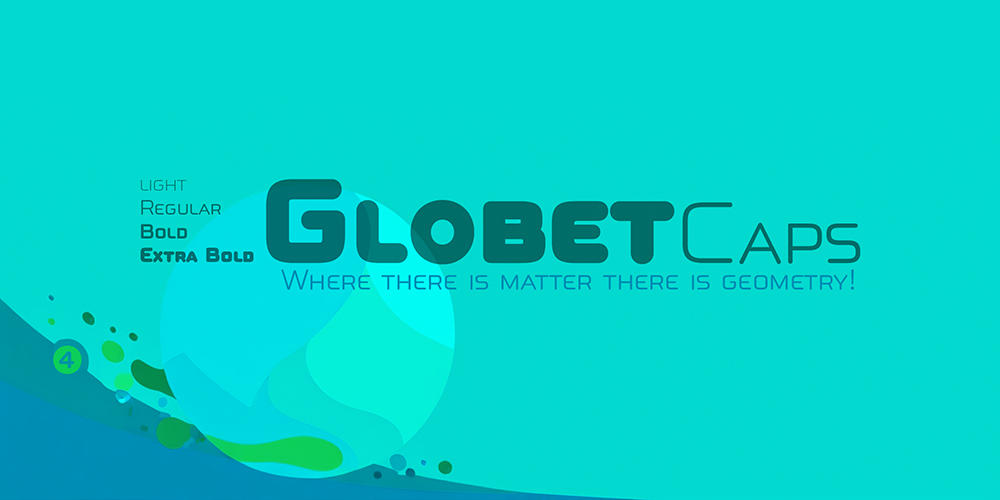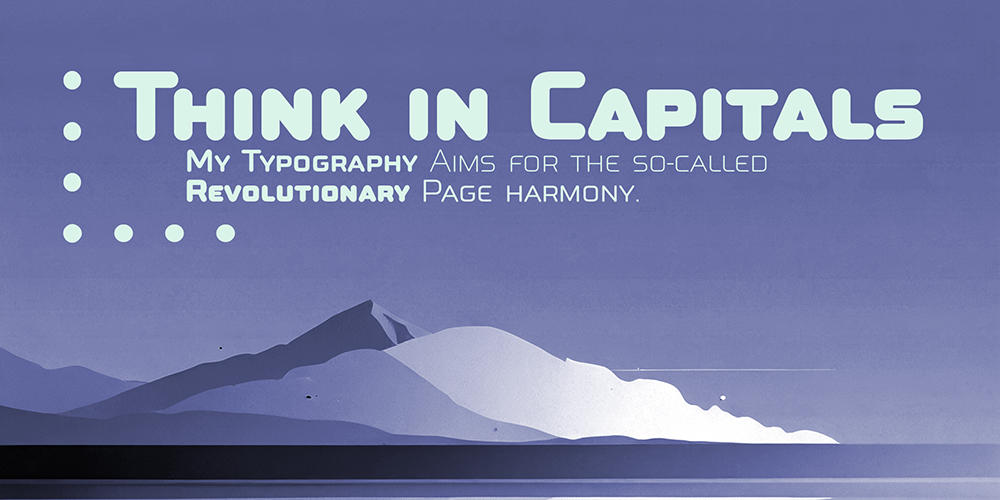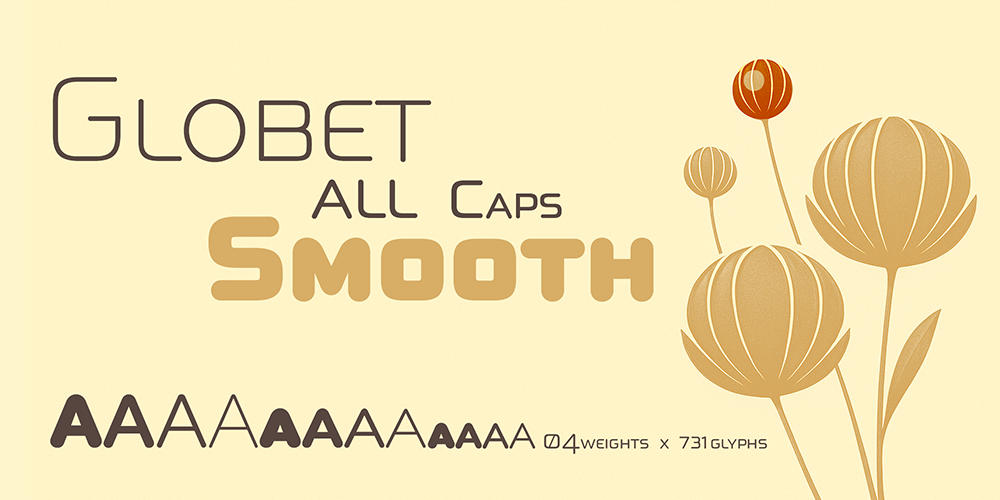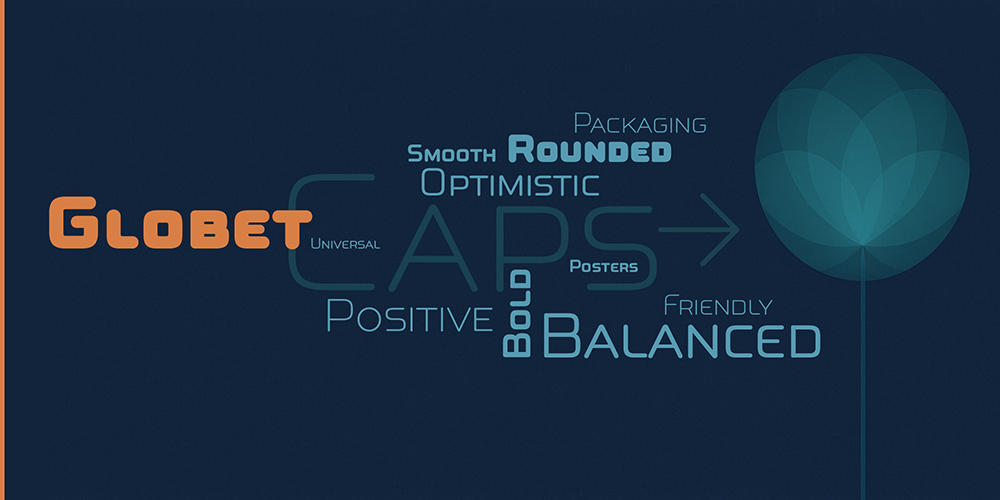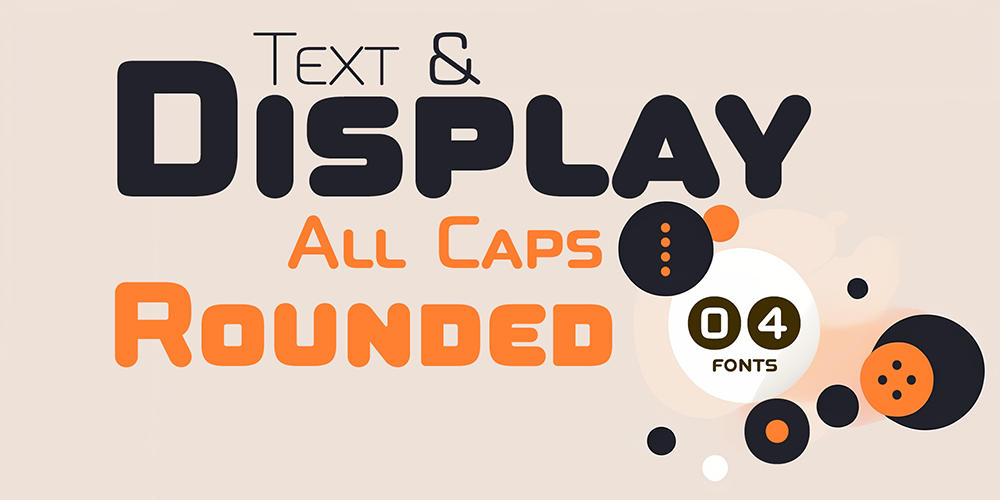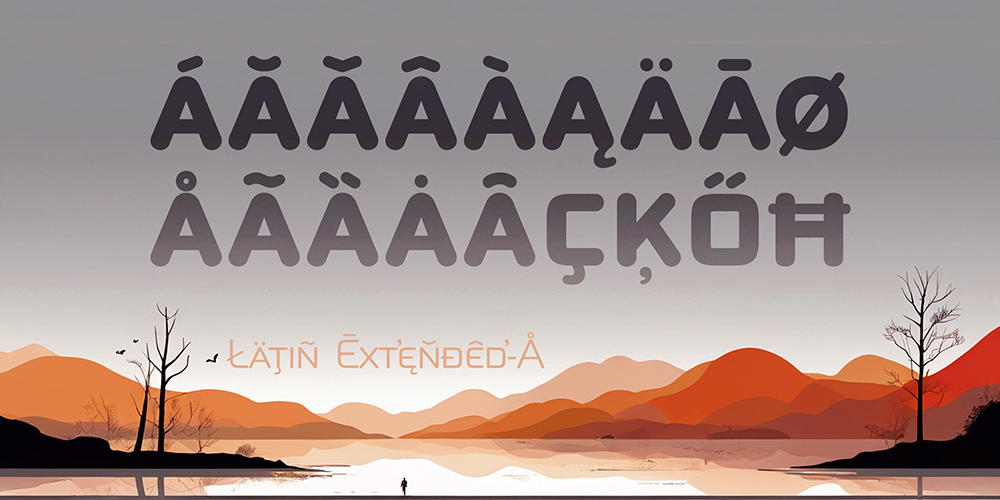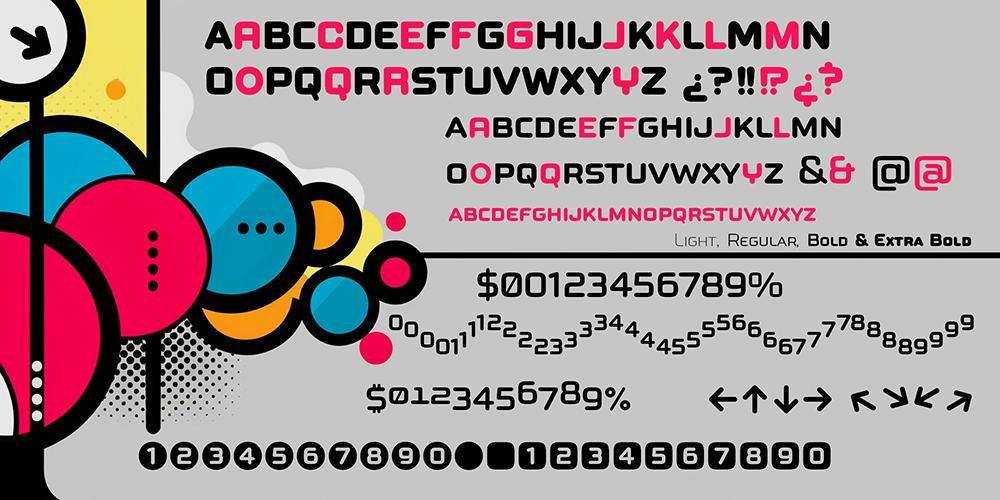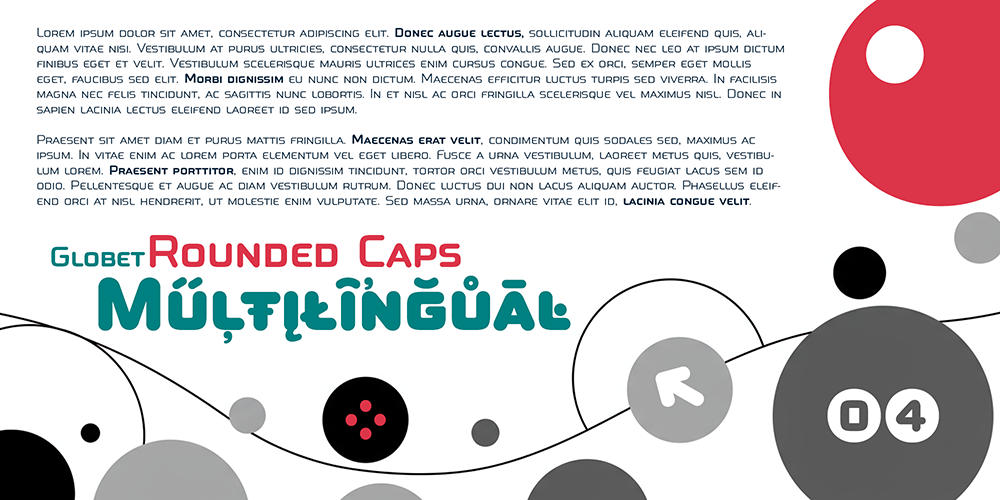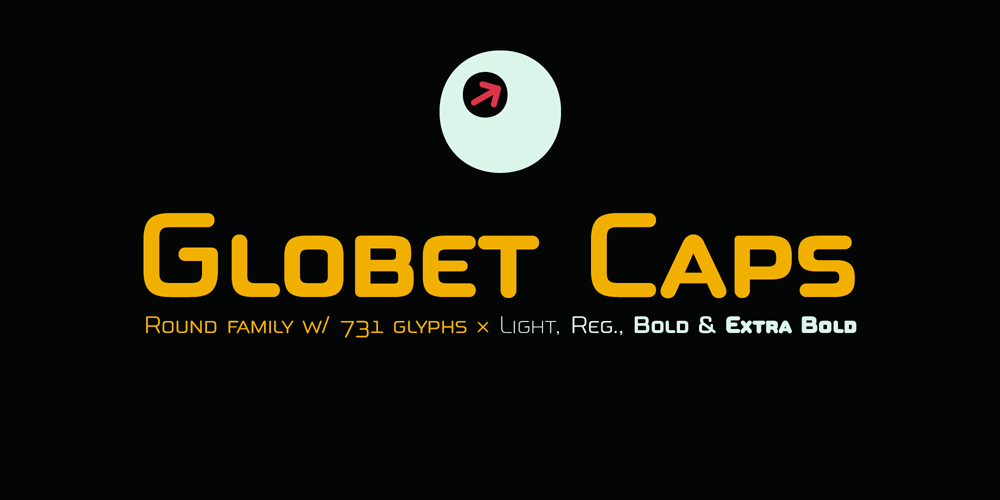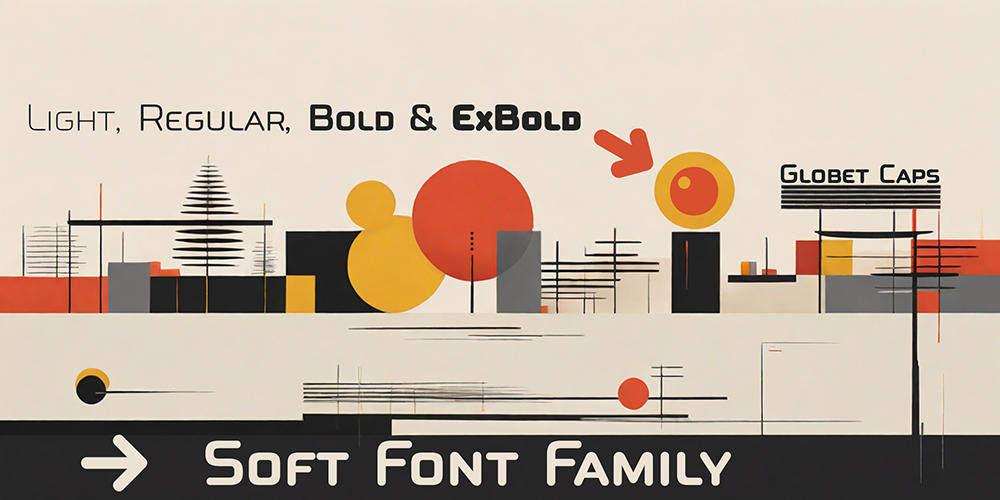
Estilo: Sans Serif, Display, Geometric, Capitals, Techno, Minimalist
Proporción: Light, Regular, Bold, Extra Bold
Alternates: 160
Autor: deFharo
Funciones OpenType: Additional languages, All Alternates, Bitcoin, Capital Spacing, Contextual Alternates, Denominators, Discretionary Ligatures, Fractions, Historical Forms, Inferiors, Kerning, Localized Forms, Numbers Small Caps, Numerators, Oldstyle Figures, Ordinals, Petite Caps, Scientific Inferiors, Slashed Zero, Small Capitals, Standard Ligatures, Stylistic Set, Subscript, Superior letters, Superiors, Superscript.
731 glyphs w/ 160 alternates: Numbers & Letters
Globet Caps: Fuerza visual con calidez
Una tipografía donde la geometría amable y la fuerza de las mayúsculas se fusionan para generar un impacto visual impecable. Diseñada como variante All Caps de Globet Round, esta familia conserva su ADN refinado: una Sans Serif redondeada, geométrica de proporciones cuadradas, compuesta exclusivamente por mayúsculas. El resultado es una fuente con una personalidad contundente, versátil y sorprendentemente cálida.
Mayúsculas que hablan con carisma
Las formas redondeadas de Globet Caps suavizan la rigidez de su estructura cuadrada, generando una voz tipográfica que transmite profesionalismo, cercanía y modernidad. Son claras sin ser frías, potentes sin ser agresivas.
Su diseño exclusivo en mayúsculas le confiere un carácter distintivo y una presencia fuerte, ideal para titulares y elementos que deben destacar visualmente. He incluido tres variantes de mayúsculas (Capitals, Small Caps y Petite Caps). Estas permiten crear jerarquías tipográficas sutiles, enriqueciendo el diseño editorial y gráfico.
Una estructura tipográfica cuidada al detalle
Con una arquitectura basada en módulos geométricos, Globet Caps presenta cuatro pesos cuidadosamente ajustados para ofrecer la máxima versatilidad en cualquier proyecto. Permitiendo adaptar la tipografía a diversas necesidades de diseño, desde un texto sutil hasta un mensaje con gran impacto visual.
- Light: Delicadeza sofisticada, ideal para textos finos o secundarios.
- Regular: Versatilidad equilibrada para cuerpos de texto y logotipos.
- Bold: Impacto seguro, perfecto para carteles y marcas fuertes.
- Extra Bold: Máxima presencia, ideal para packaging, señalización y branding audaz.
Legibilidad y equilibrio visual
Durante el proceso de diseño, apliqué correcciones ópticas meticulosas para asegurar que cada bloque de texto conserve un peso visual uniforme. El ajuste preciso de métricas y kerning garantiza que tanto textos breves como grandes titulares se perciban siempre claros, firmes y estéticamente equilibrados. Cada letra fluye armoniosamente con la siguiente, permitiendo una experiencia de lectura fluida, sin importar el tamaño del texto ni el medio en el que se utilice.
Tecnología tipográfica avanzada
Globet Caps no solo destaca por su estética, sino también por su sólida estructura técnica. Gracias a sus funciones avanzadas OpenType, ofrece un abanico de herramientas creativas para potenciar cualquier proyecto:
- Letras y números alternativos: Para personalizar palabras y composiciones con estilo propio.
- Fracciones dinámicas y signos matemáticos: Esenciales en contextos técnicos o científicos.
- Flechas geométricas: Coherentes con el estilo de la fuente, ideales para señalización o infografías.
- Small Caps y Petite Caps: Perfectas para jerarquizar información en textos editoriales complejos.
- Soporte multilingüe (Latin Extended-A): Cobertura amplia para proyectos internacionales.
Mayúsculas para todo
Globet Caps ha sido diseñada como una tipografía multipropósito, ideal para una amplia gama de aplicaciones creativas:
- Diseño editorial: Títulos de revistas, portadas de libros y maquetaciones tipográficas.
- Folletos, pósters y cartelería: Mensajes llamativos y legibles al instante.
- Branding e identidad visual: Logotipos sólidos, con una presencia fuerte y coherente.
- Packaging de productos: Para destacar con personalidad en puntos de venta.
- Señalética y sistemas de información gráfica: Claridad, orden y profesionalismo en espacios urbanos.
Tipografía con voz propia
En resumen, Globet Caps es una tipografía que fusiona la estética geométrica con la calidez visual de las formas redondeadas y la potencia comunicativa de las mayúsculas, aportando a la vez, un tono humano, una voz geométrica sin aristas, rica en matices, unas letras que transforman la sobriedad estructural en comunicación directa y moderna.
Ideal para diseñadores que buscan equilibrio entre racionalidad visual y emoción comunicativa.